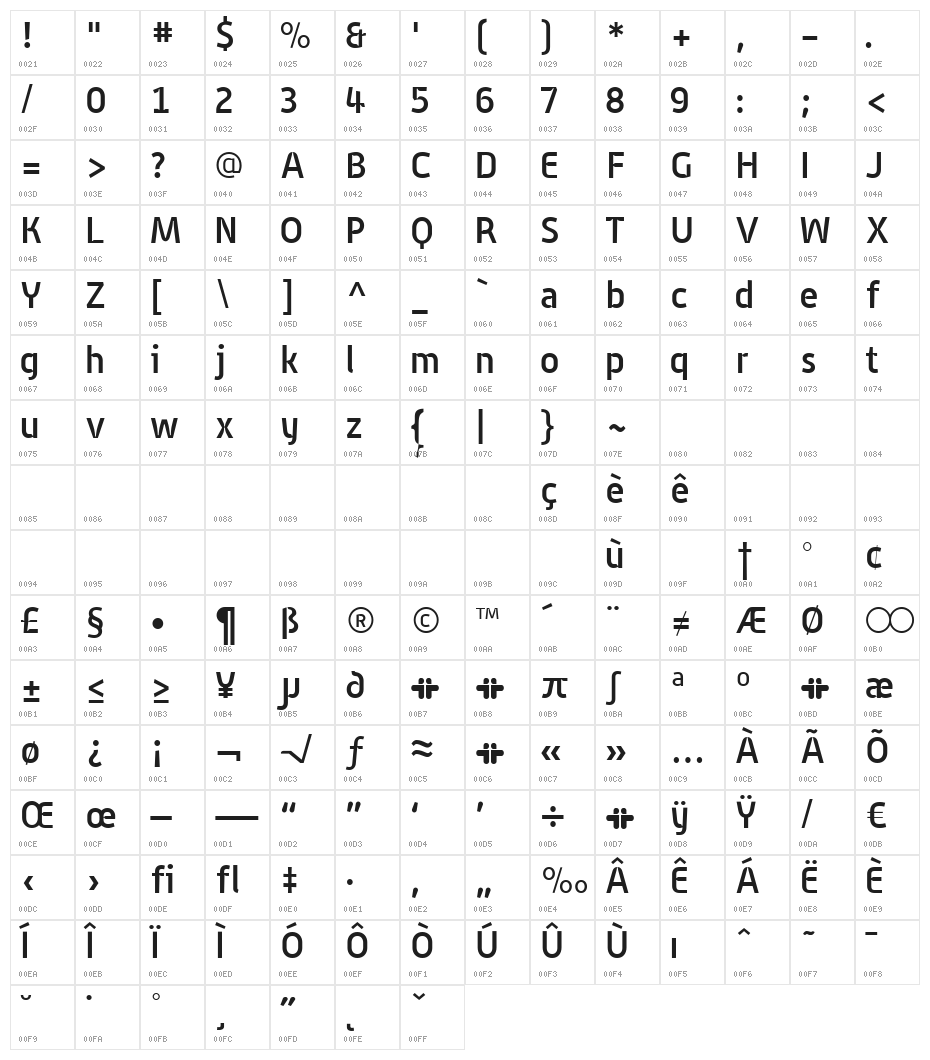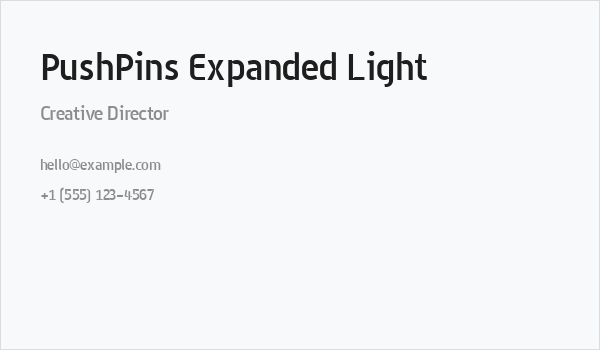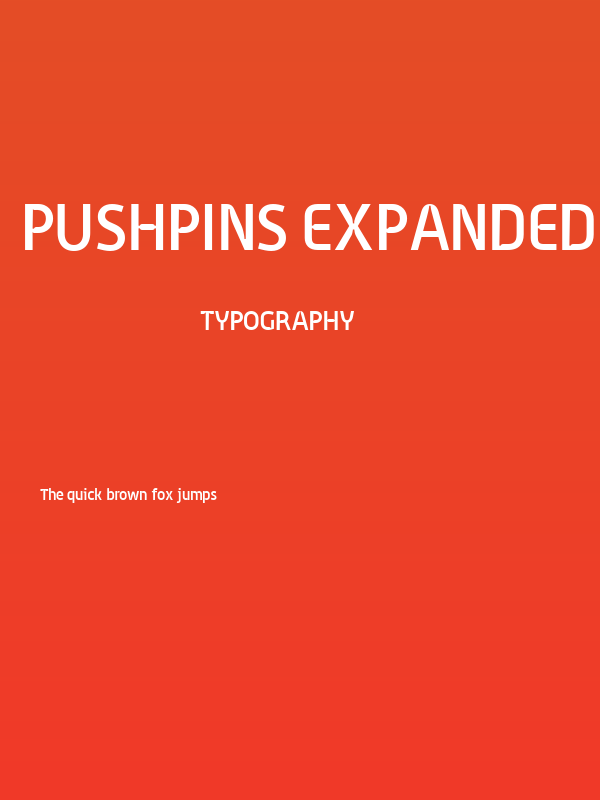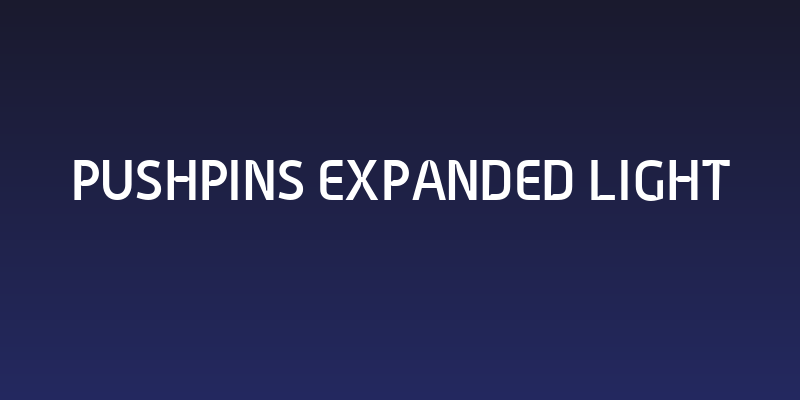
PushPins Expanded Light Font
| Progetti proposti | Ideal for branding, advertising, web design, and editorial projects where a modern and clean aesthetic is desired. |